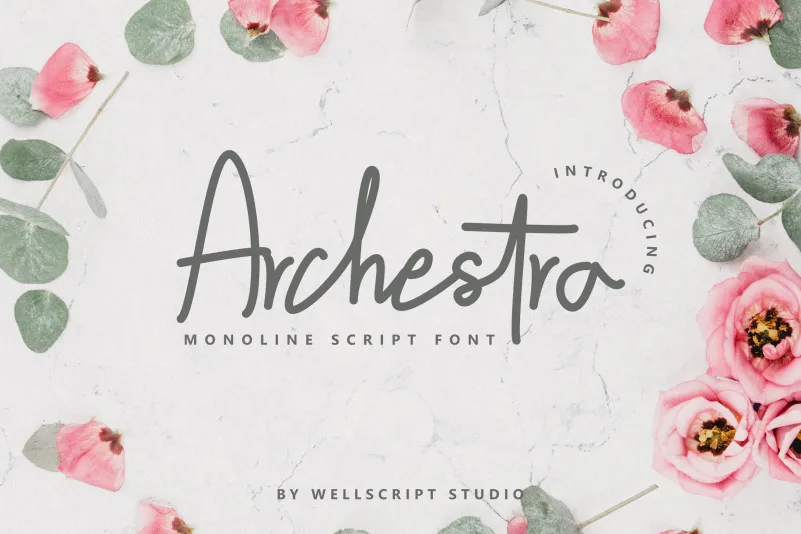
Archestra – Handwritten Script Font – Fonte Grátis
Archestra - Handwritten Script Font
Archestra é uma elegante fonte de estilo script monolineada que transmite um ar de sofisticação através de sua forma minimalista e natural. Ela captura a essência das letras escritas à mão, apresentando uma linha única com uma fluidez contínua e um aspecto orgânico único, criando um padrão de estilo autêntico ideal para gráficos de destaque como assinaturas. Este é o tipo de fonte que torna suas criações inegavelmente atraentes e personalizadas, especialmente quando você usa-a em seu trabalho de design de gráficos ou marketing digital. A designer do Archestra, da wellscriptstudio, tem claro noção de como criar uma impressão forte e única que se destaca no mercado dos recursos digitais.